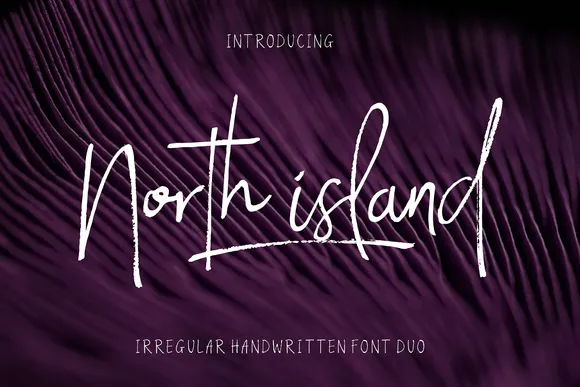
A North Island Font é uma fonte aquarelada criada pelo Zerowork Studio, disponível no CreativeMarket. Ela se destaca entre outras fontes graças à sua natureza artesanal e sofisticada. Este tipo de letra reflete os traços de uma escrita feita a mão, permitindo que você enriqueça suas criações profissionais com um toque único e interessante. Com dois estilos distintos de fonte e swashes como personagens amplificadores, o North Island Font oferece-lhe ainda mais opções para personalizar seu design. E por não querer deixar seu trabalho sem brilho, a equipe adicionou uma coleção especial de formatos Photoshop gratuitamente, com um toque de estética extra aos seus projetos. Esta fonte é perfeita para quem busca dar um toque diferente e único em suas criações digitais. Ela pode ser usada tanto no design gráfico quanto em publicações online, mantendo seu trabalho profissional ao mesmo tempo que se torna mais atraente e interessante aos olhos do leitor. Não perca esta oportunidade de enriquecer sua arte digital com a North Island Font.